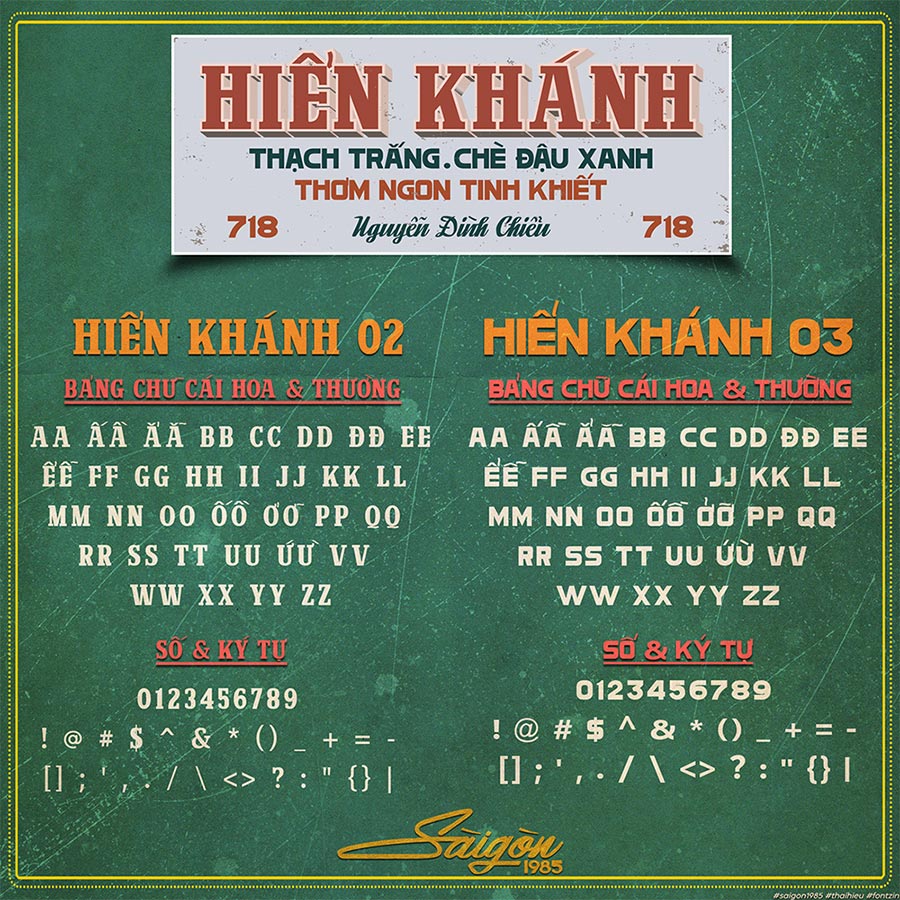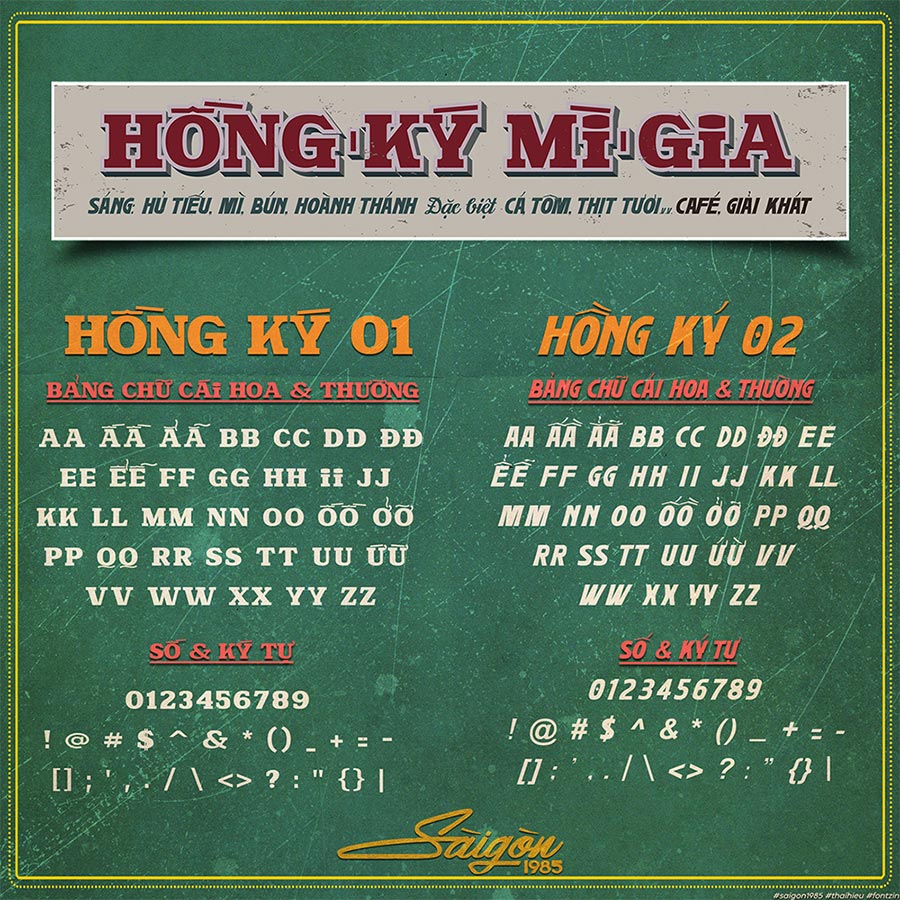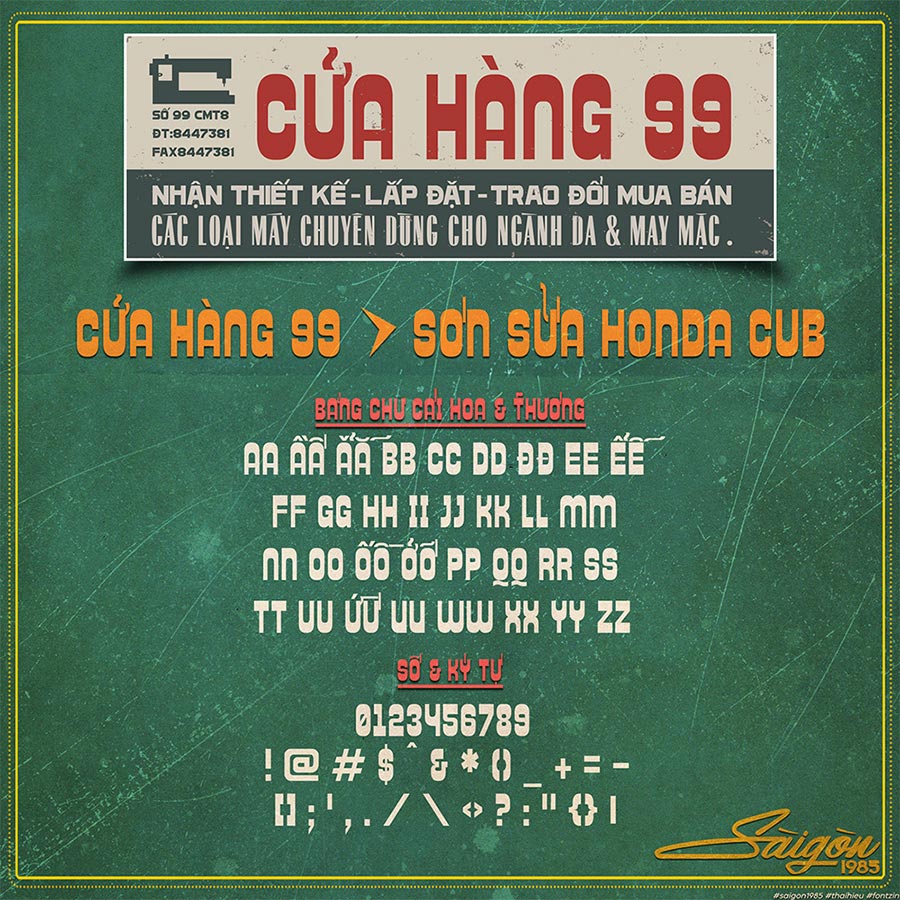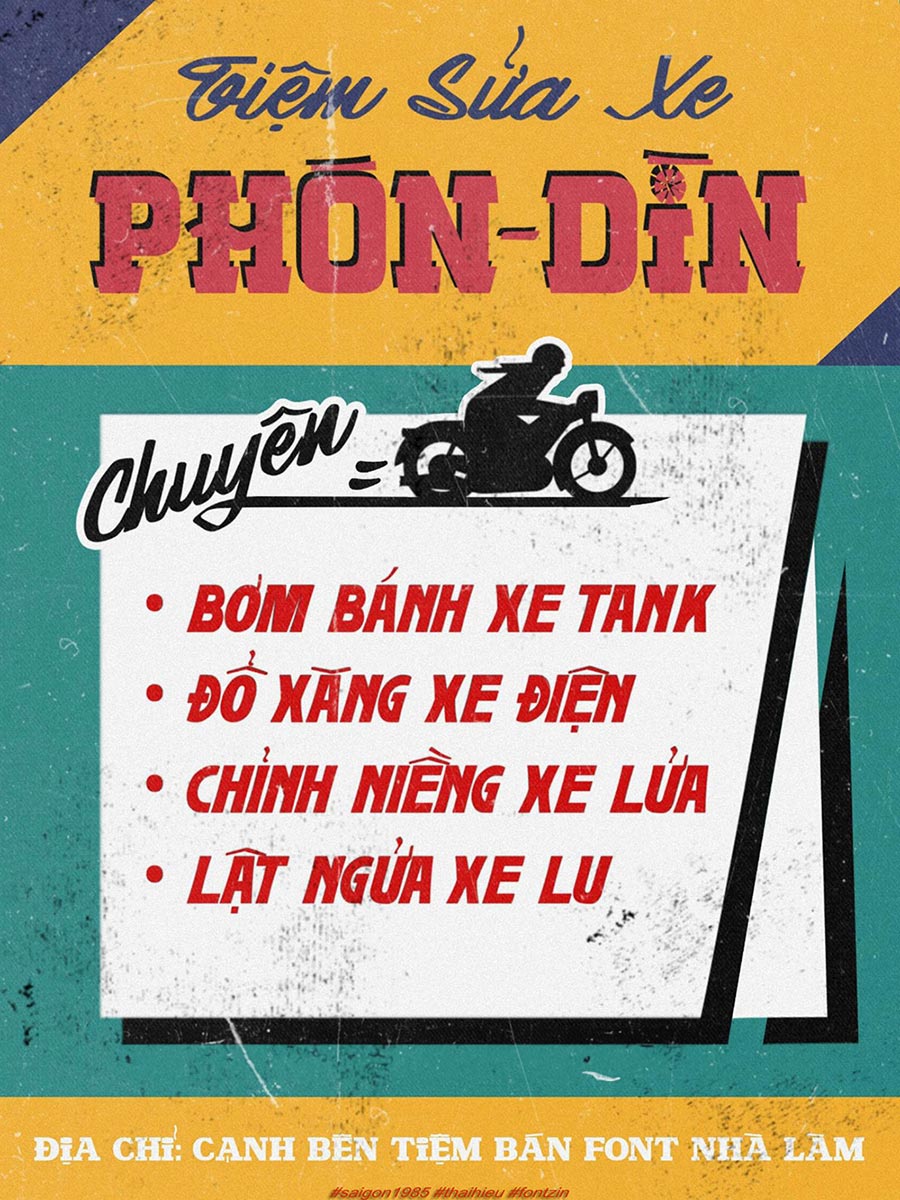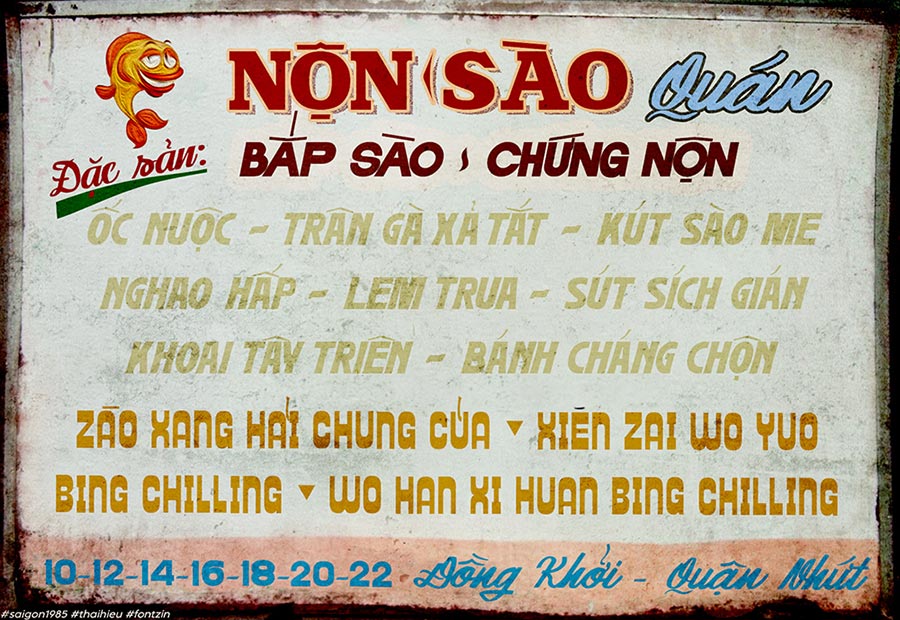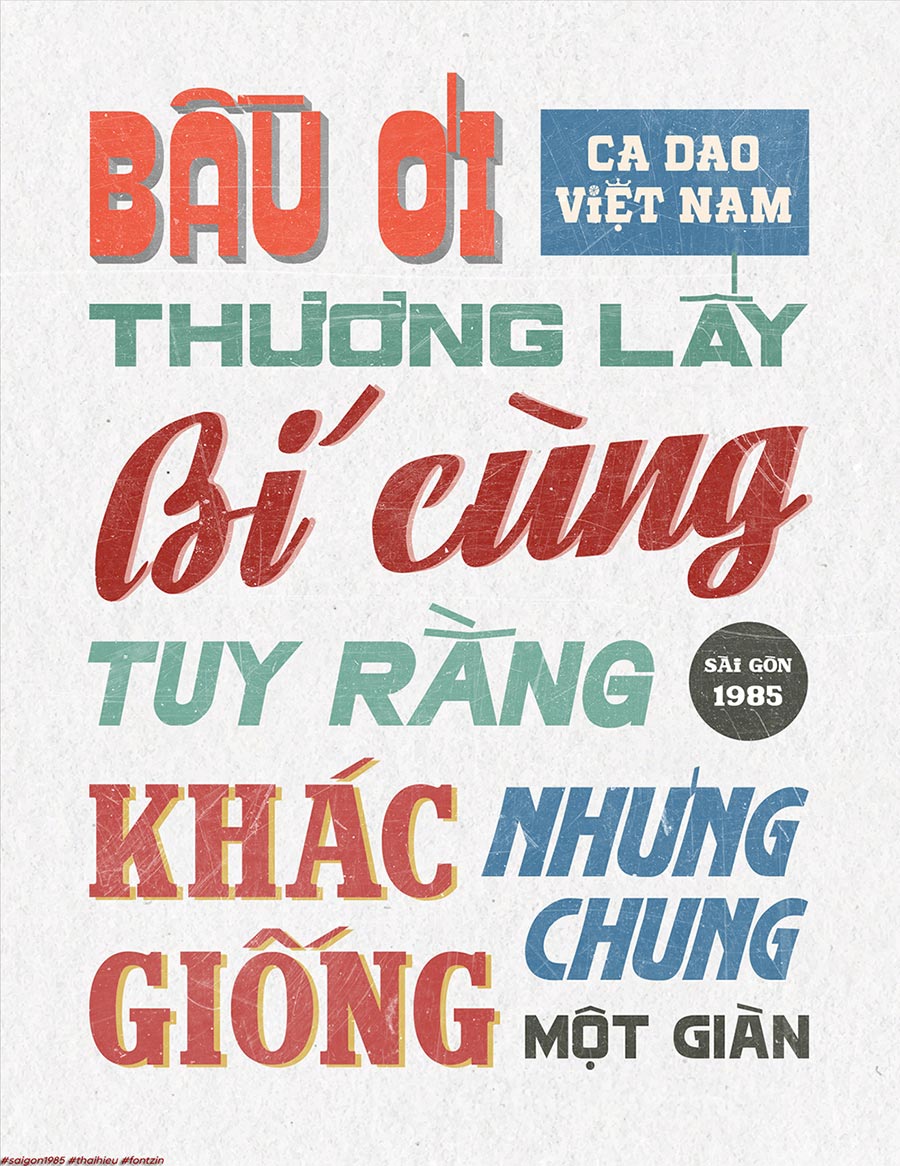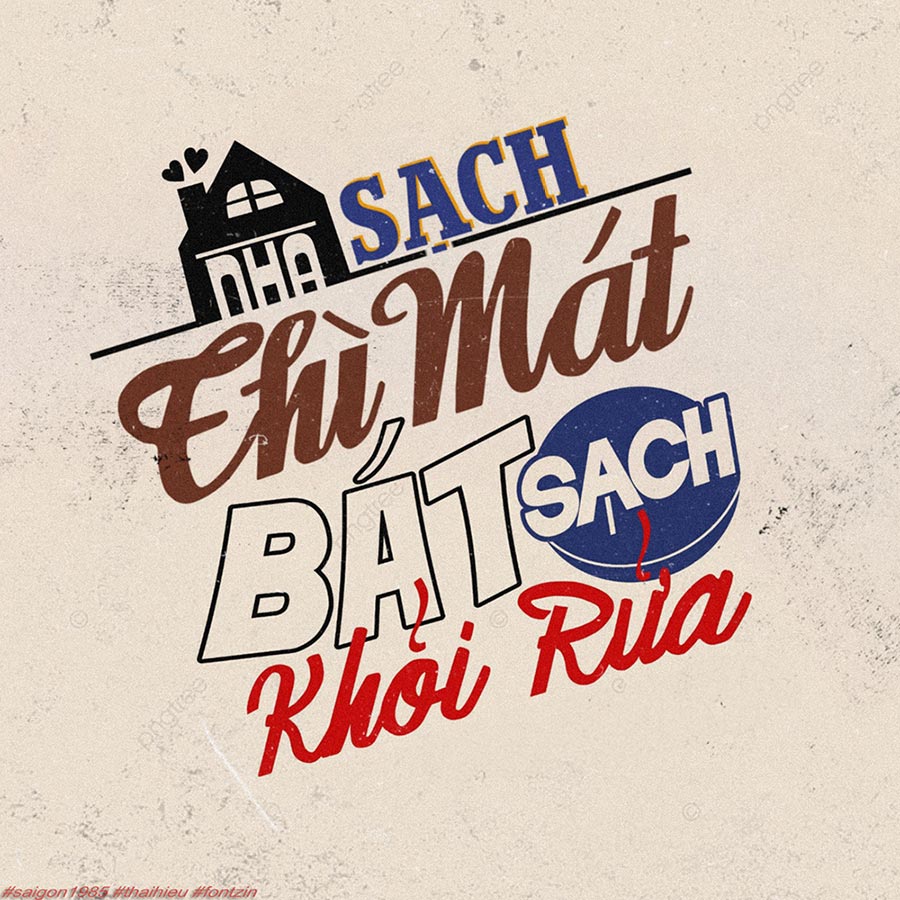
Chia Sẻ Miễn Phí Font Chữ Sài Gòn Cổ Điển Xưa 1985
Sadesign, một đơn vị uy tín trong lĩnh vực thiết kế sáng tạo, đã chính thức chia sẻ miễn phí font chữ mang phong cách Sài Gòn cổ điển năm 1985. Đây là một bước đi đầy ý nghĩa, không chỉ giúp các nhà thiết kế tiếp cận với một tài nguyên giá trị mà còn góp phần lan tỏa vẻ đẹp văn hóa của một thời kỳ đáng nhớ.
1. Ý nghĩa của font chữ Sài Gòn cổ điển 1985
Trong bối cảnh hiện nay, khi nhu cầu tái hiện và giữ gìn những giá trị văn hóa truyền thống ngày càng được chú trọng, việc phục dựng các yếu tố thiết kế mang tính di sản đang trở thành xu hướng được nhiều nhà thiết kế và người yêu nghệ thuật quan tâm. Một trong những yếu tố quan trọng góp phần tạo nên bản sắc văn hóa chính là font chữ - công cụ không thể thiếu trong thiết kế đồ họa và truyền thông.
Font chữ Sài Gòn cổ điển năm 1985 mang trong mình hơi thở của một giai đoạn lịch sử đặc biệt. Được lấy cảm hứng từ phong cách thiết kế bảng hiệu, biển quảng cáo và các tài liệu in ấn phổ biến tại Sài Gòn những năm 80, font chữ này tái hiện lại nét hoài cổ, mộc mạc nhưng không kém phần tinh tế. Đây là loại font không chỉ thể hiện sự sáng tạo mà còn gắn liền với ký ức và tâm hồn của nhiều thế hệ người Việt.
2. Ứng dụng trong thiết kế hiện đại
Font chữ này không chỉ phù hợp cho các dự án thiết kế mang tính hoài niệm, mà còn có thể được ứng dụng linh hoạt trong các lĩnh vực như quảng cáo, thiết kế thương hiệu, bao bì sản phẩm hoặc các chiến dịch truyền thông hướng về giá trị truyền thống. Với đặc trưng độc đáo và sự tinh tế trong từng đường nét, font chữ này giúp các nhà thiết kế tạo nên những sản phẩm vừa đậm chất nghệ thuật vừa mang tính gợi nhớ.
Việc chia sẻ miễn phí font chữ Sài Gòn cổ điển xưa 1985 của Sadesign không chỉ là một hành động mang tính nhân văn mà còn là cầu nối giữa quá khứ và hiện tại. Nó giúp gợi nhắc những giá trị văn hóa đặc sắc của Sài Gòn xưa, đồng thời khuyến khích các nhà thiết kế trẻ sáng tạo trên nền tảng di sản truyền thống. Đây chắc chắn sẽ là một đóng góp ý nghĩa cho cộng đồng sáng tạo và văn hóa Việt Nam.